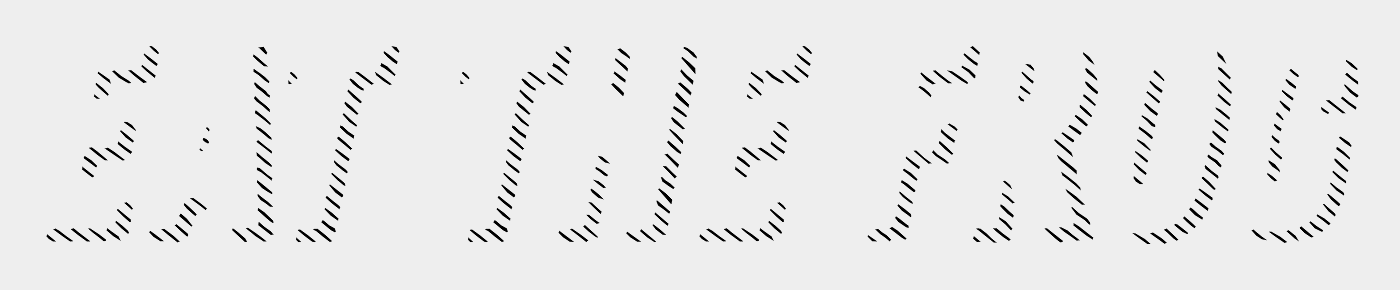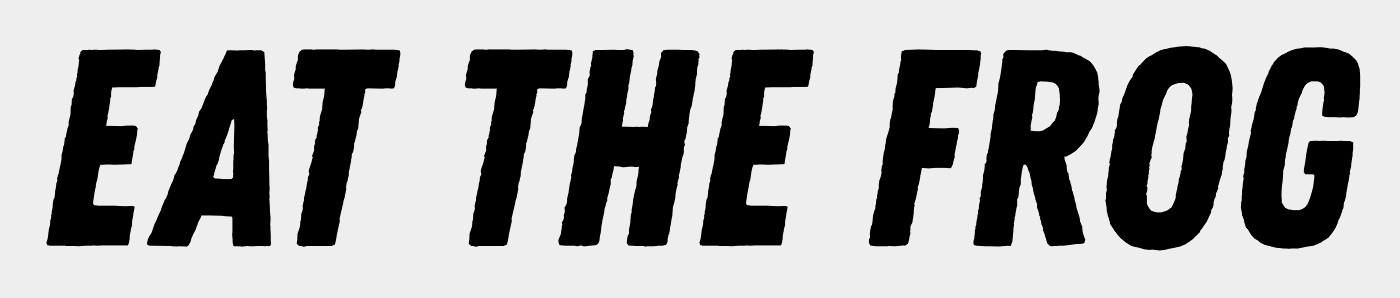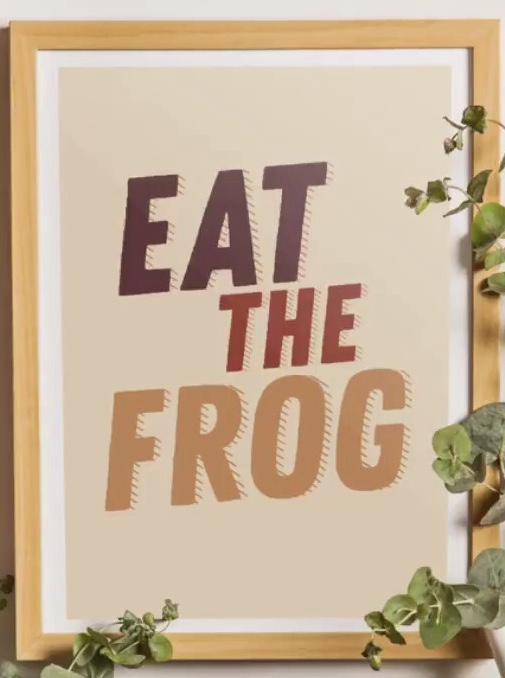
Suche Die Schriftart von folgendem unbekannten Plakat (Eat the frog) Ähnlich zu ZING Rust Base Shadow 4?!
Hallo ich habe folgenden Screenshot geschickt bekommen und finde die Schriftart toll.
Herkunft und Zeitpunkt ist leider unbekannt, ein paar Jahre ist es her.
Suche diesen oder ähnlichen Font. am besten kostenlos.
Die Zing Rust gibt es ja in unzähligen kombinierbaren verschiedenen Varianten … aus den beiden mit bissl Nachbearbeitung bringt man das gut hin. Ich kann (und möchte) mir nicht vorstellen, dass der Gestalter das einfach nur gesetzt hat.